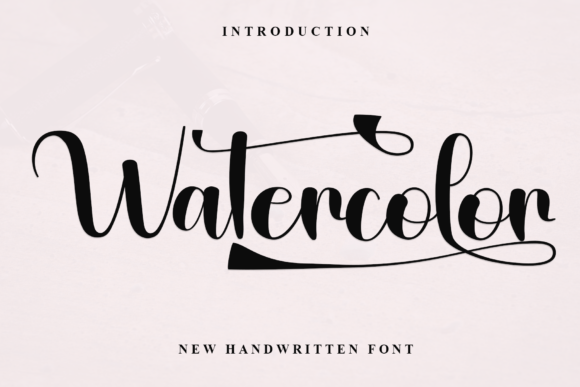
Watercolor
適切なデザイン要素を見つけるのは難しい場合がありますが、Watercolorは作品を即座に引き立てる優れたコレクションを提供します。
精密に作られたWatercolorは、クリーンなベクター、滑らかなタイポグラフィ、そして安心のための商用ライセンスを提供します。
POD(オンデマンド印刷)製品、結婚式の招待状、またはソーシャルメディアのグラフィックを作成している場合でも、Watercolorは理想的です。